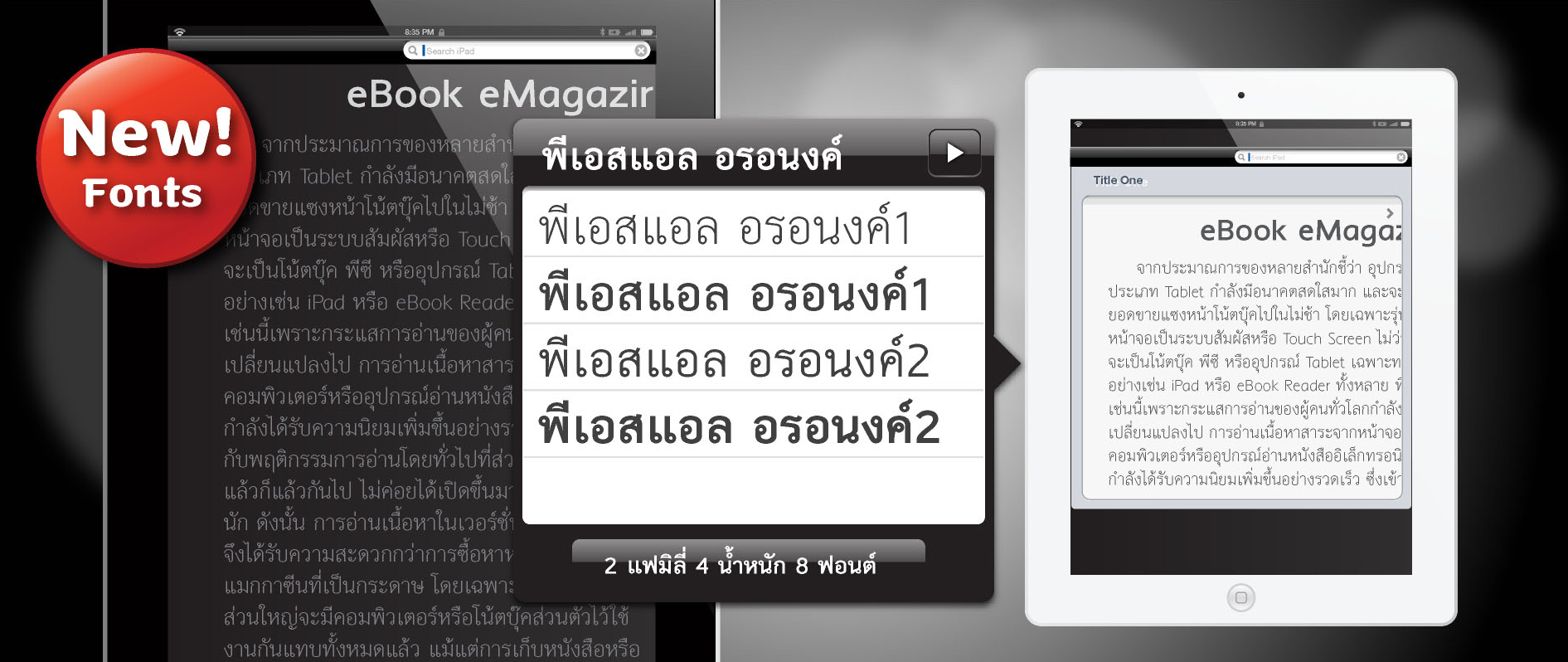
อุ๊ย ฟอนต์เดจาวู
บางทีก็ไม่ค่อยเข้าใจขอบเขตของการลอก แรงบันดาลใจ หรือคำไหนดี
คือสงสัยจริงๆ นะ รู้สึกว่าหลายฟอนต์ที่คล้ายกับฟอนต์อื่นมากจนถ้าเราเป็นเจ้าของฟอนต์ต้นฉบับก็คงไม่ค่อยสบายใจนัก
เจ้าของฟอนต์ไม่ค่อยซีเรียสนะครับ จากการไปแอบถามมา
ดูจากรูปพรีวิวฟอนต์...  :09: :09:
ถ้ากล้าที่จะให้เป็น Device Font ก็ต้อง Hinting ดี และต้องรองรับ latin2 ที่สำคัญต้องจัดการเรื่องวรรณยุกต์ให้ดี
อย่าง AIS Bookstore เอา Helvethaica มา Embed ใส่ใน Ookbee วรรณยุกต์มันลอยนะ เพราะ iOS ไม่ได้รองรับสคริปต์ liga
เออ น่าสนป่ะ เอาฟอนต์ฟรีที่มีคุณภาพ ไปพัฒนาสำหรับ App บน iOS เอย Android เอย
แล้วที่ PSL ปล่อยตัวนี้ออกมา เขาคิดยังไงอ่ะ  :44: :44:
มันดู จงใจ มากไปมะ คือ สายตาเราแทบจะแยกไม่ออกเลยอ่ะ
ขนาดตาเราแบบว่า ส่องดีเทลมาหลายต่อหลายฟอนต์
เซ็ตละติน เป็นแบบที่ไม่เหมือนสารบัญ
อ่ะ ง งู ไม่เหมือนอ่ะ ตัวอื่นละ ลองส่องกันซิ มีไรต่างอีก
ชอบละตินตัวนี้มากกว่านะครับ
แต่ภาษาไทยนี่เป๊ะจนแปลกใจอะ
ชอบละตินตัวนี้มากกว่านะครับ
เหมือนกันนิ